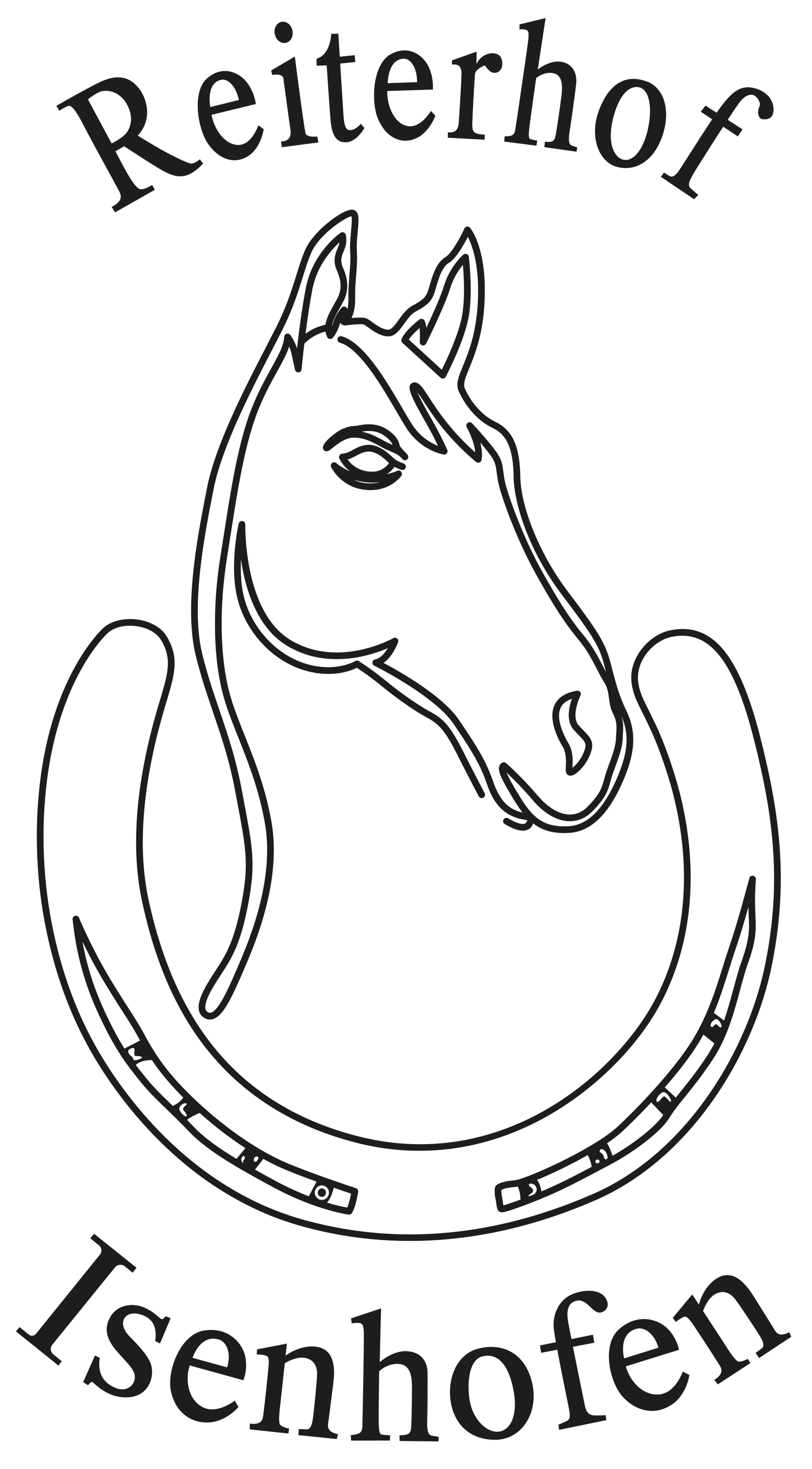
Suche Schriftart des Logos vom "Reiterhof Isenhofen"
kennt jemand die Schriftart des Logos vom "Reiterhof Isenhofen"?
Es handelt sich um einen Reiterhof aus Bayern.
Das Logo soll erneuert werden, die Schriftart soll aber gleich bleiben.
Eine ähnliche Schriftart, die kostenlos ist, wäre perfekt.
Die Buchstaben unten sehen sehr nach einer Times aus. Der Text oben ist horizontal gequetscht.
Gegen eine Times spricht allerdings die Form des »R« und des »t«s.